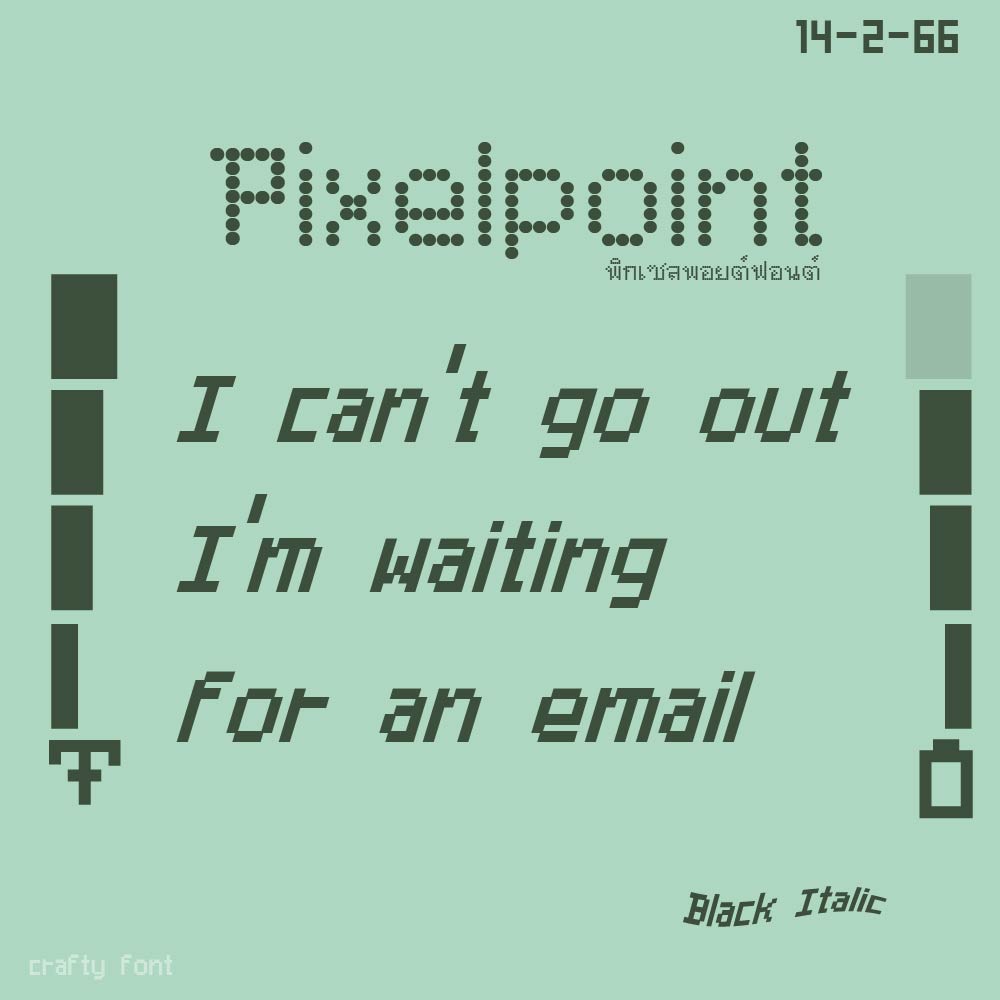
ฟอนต์ Pixelpoint
ภาพแรก :
ฟอนต์พิกเซลพอยต์ มาในรูปแบบตัวเม็ดพิกเซลสุดคลาสสิก พัฒนาต่อจากฟอนต์พิกเซลเล็ตให้มีหัว  หื่น ยังคงพยายามอย่างยิ่งไม่ให้น้องตัวอ้วนเกินไป เลยมีการโกงเม็ดพิกเซลบ้างเล็กน้อย ฮิๆ คริคริ
พิกเซลพอยต์ มีตัวปกติ (เม็ดพิกเซลกลม) ตัวหนา ตัวทึบ ตัวเอียง และตัวทึบเอน
***ฟอนต์ Pixelpoint ภาษาไทยไม่มีเลขไทยนะคะ แต่สามารถพิมพ์ได้ปกติค่ะ จะแสดงผลเป็นเลขอารบิกค่ะ
Created by Jilada Ritkhamrop
555 ท่านประธานมีร้อง
จองครับ เร่งให้ถึงหน้า10 อิอิอิ
จองค่าาาาา